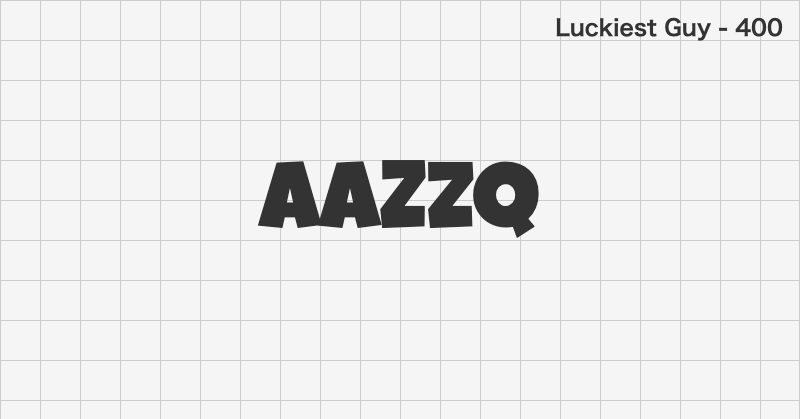
Luckiest Guy は、1950年代の広告からインスパイアを受けた、フレンドリーな印象のゴシック体フォントです。太く、力強い線が特徴で、視覚的にインパクトを与えるデザインです。
Luckiest Guy は、アメリカ・シカゴを拠点とするタイプファウンドリー Astigmatic によってデザインされ、1950年代の手書きの広告スタイルを再現することを目的としています。ユニークなデザインは、さまざまなプロジェクトに適しています。